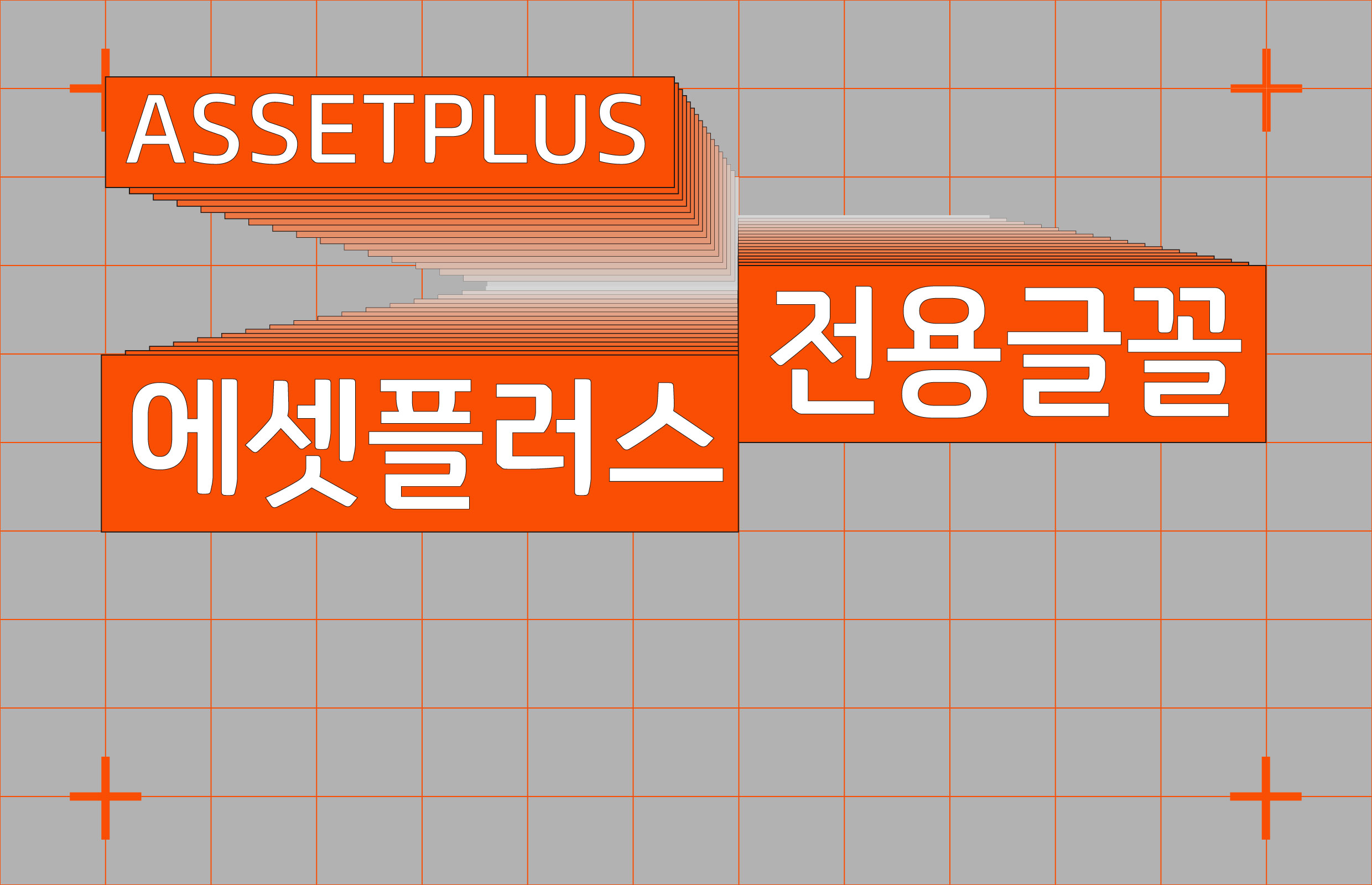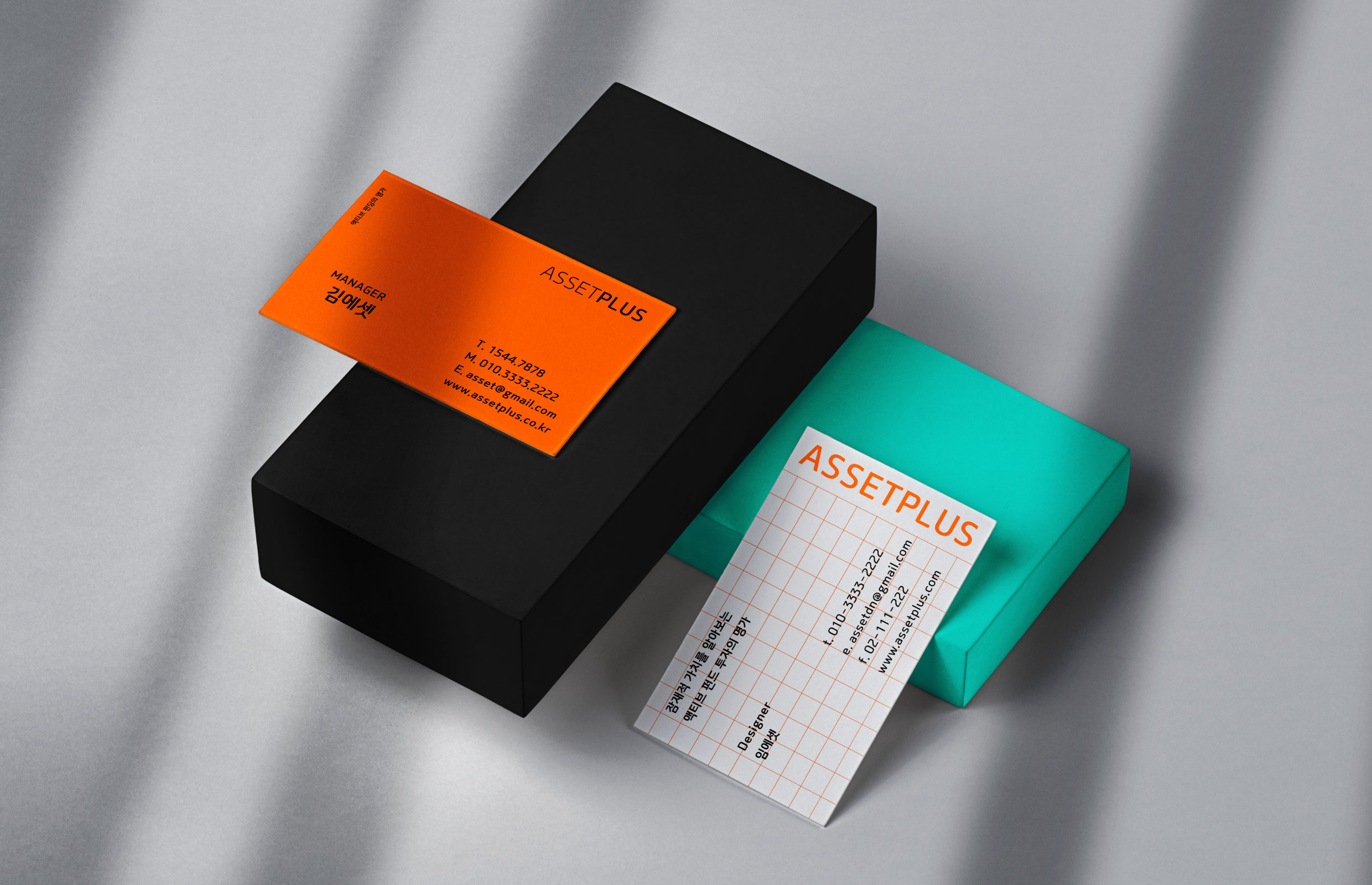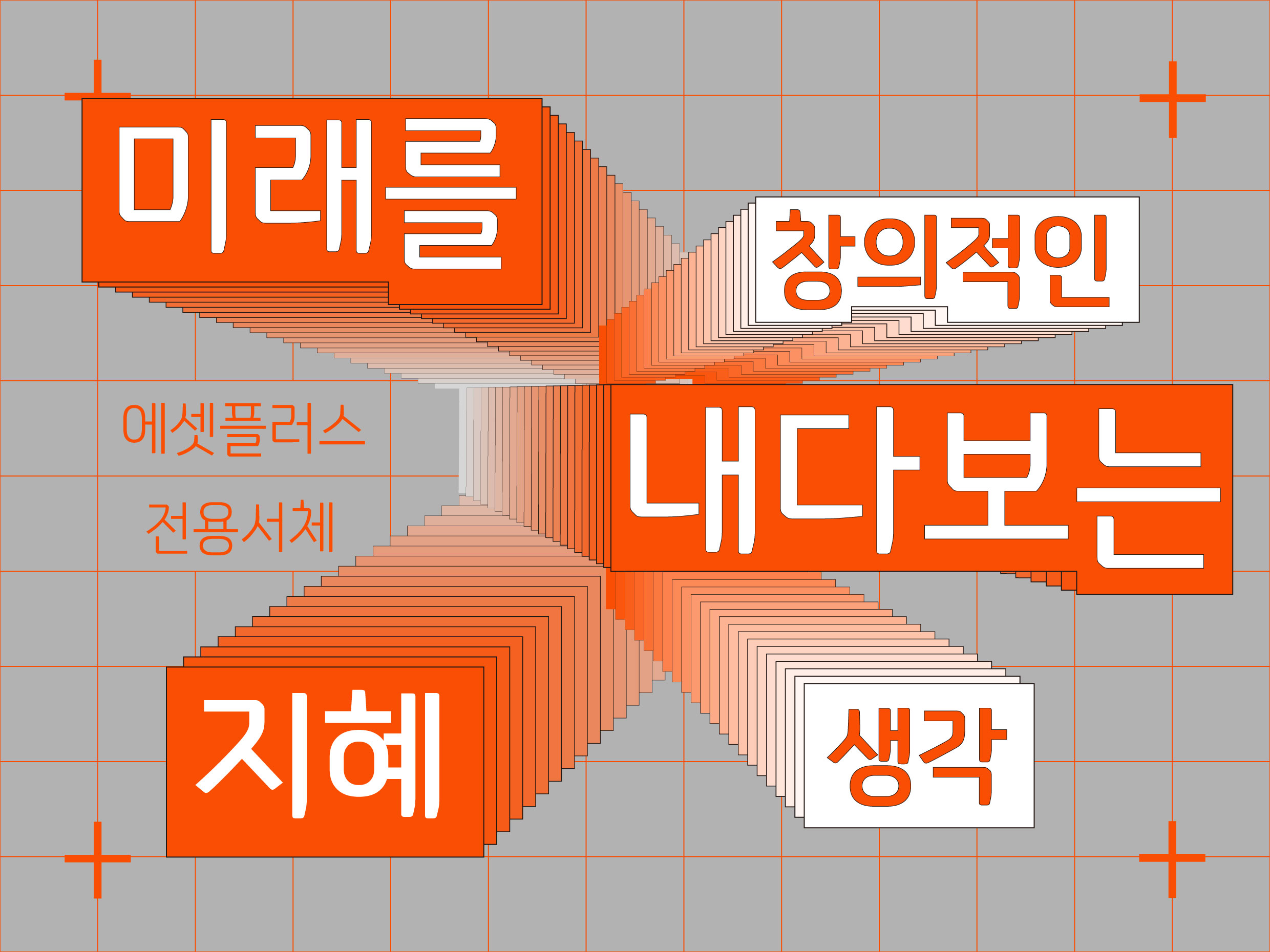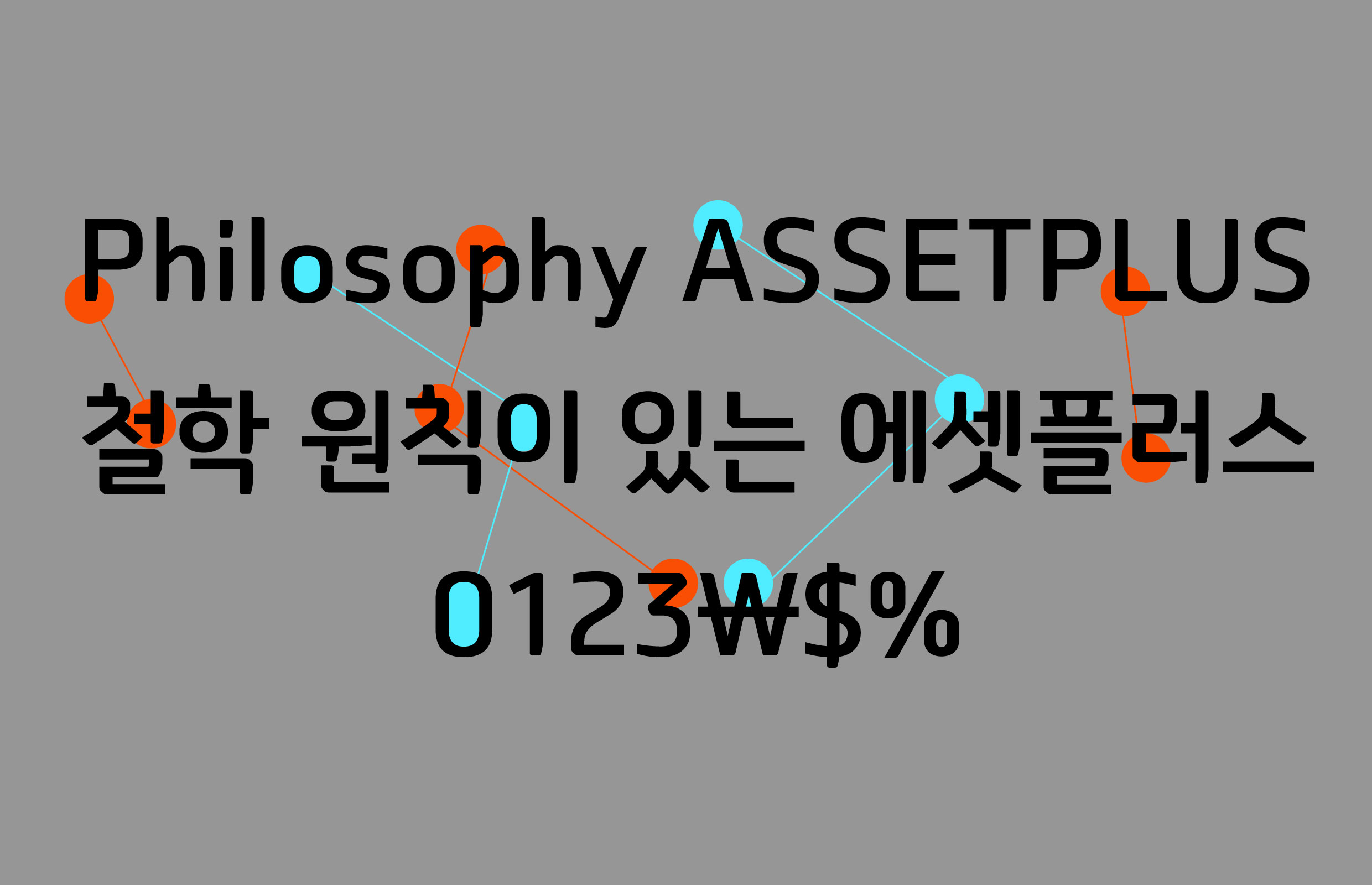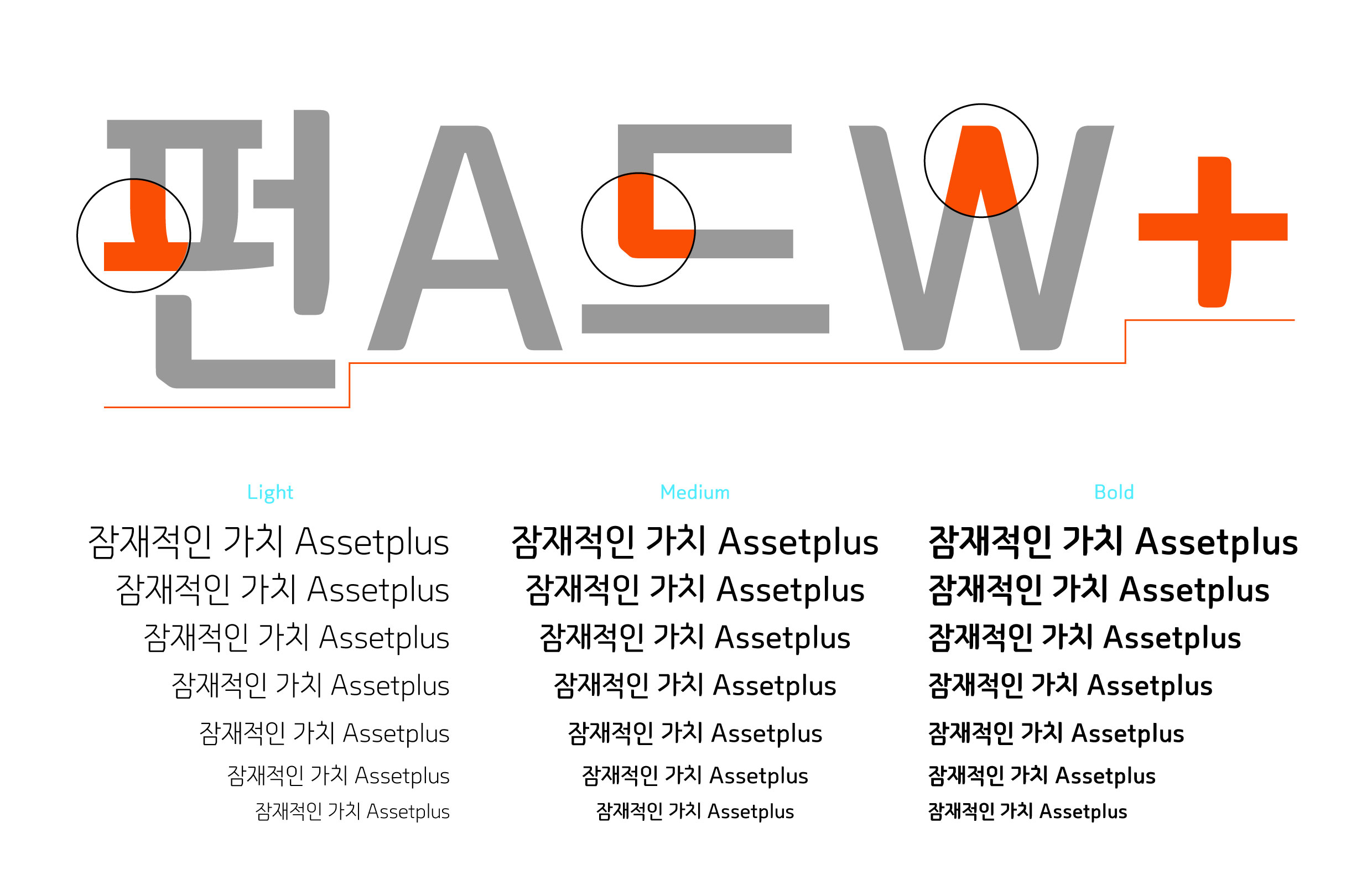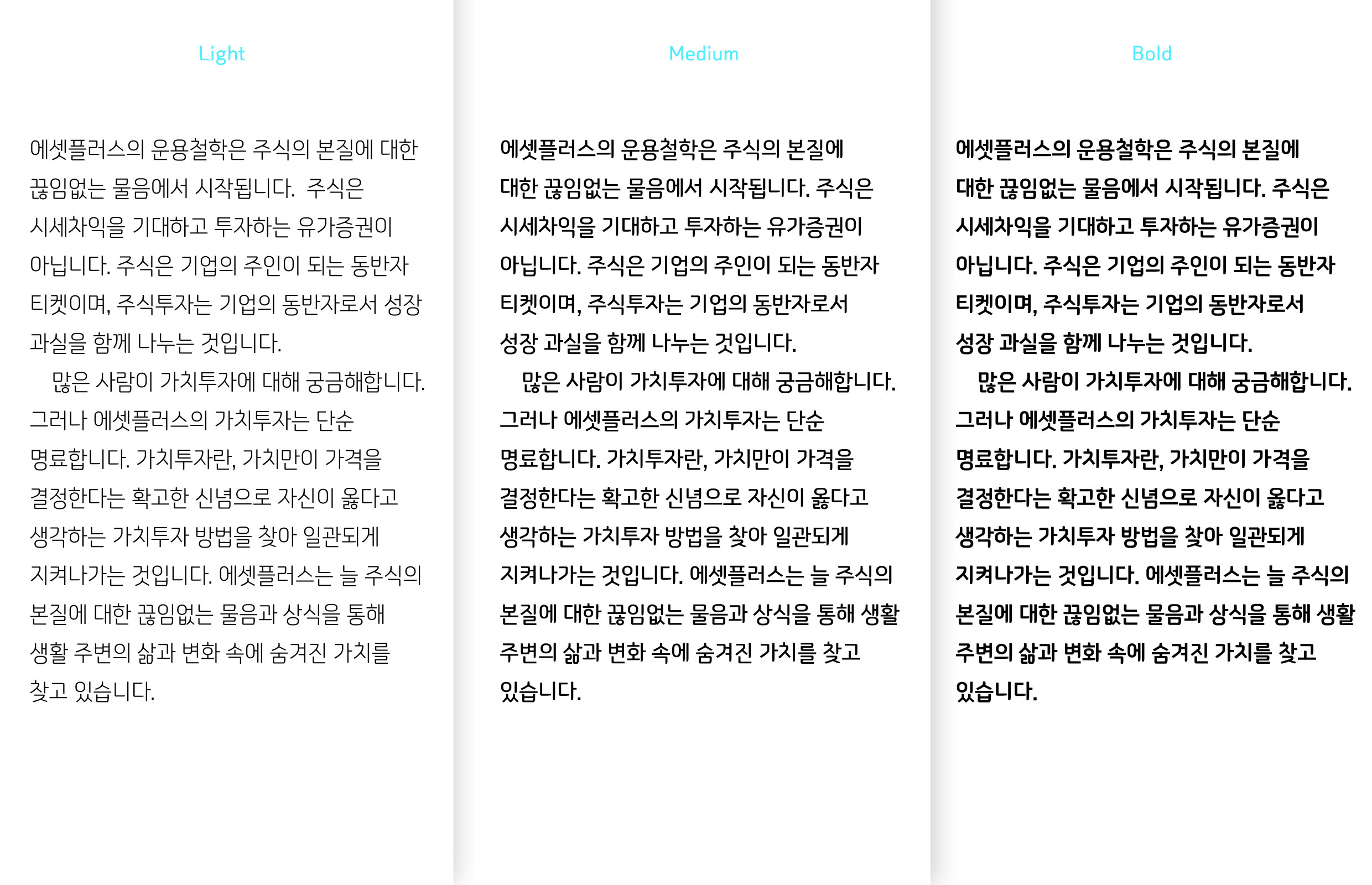
에셋플러스자산운용 [에셋플러스 전용서체]
‘미래를 내다보는 지혜’, ‘창의적 생각’ 등 에셋플러스가 추구하는 방향성을 서체로 표현한 프로젝트. 자산운용사가 가져야 할 신뢰감과 투명함, 모던함을 표현하기 위해 고딕 스타일을 취하였고, 더 나은 미래로 상승하는 이미지를 각 자소에 디자인 요소로 적용하였다.